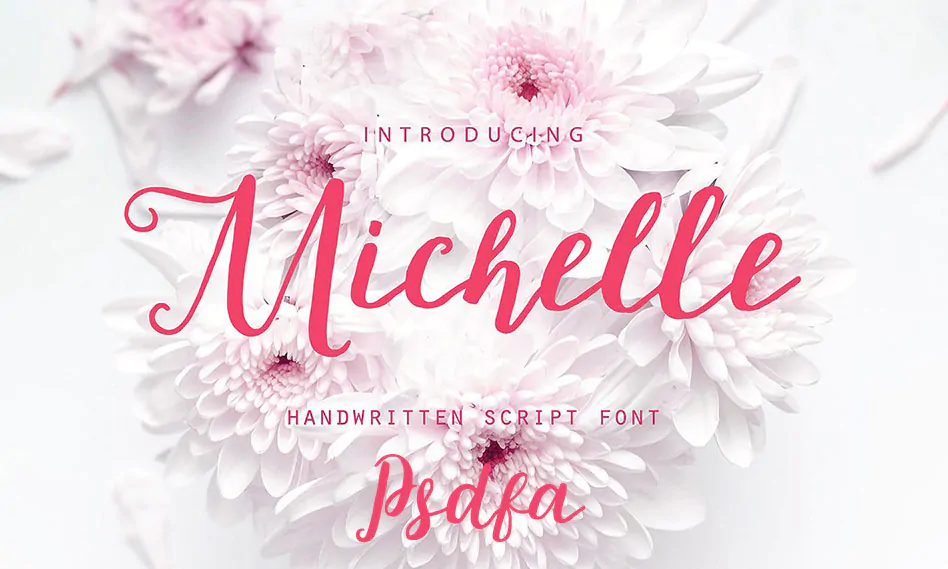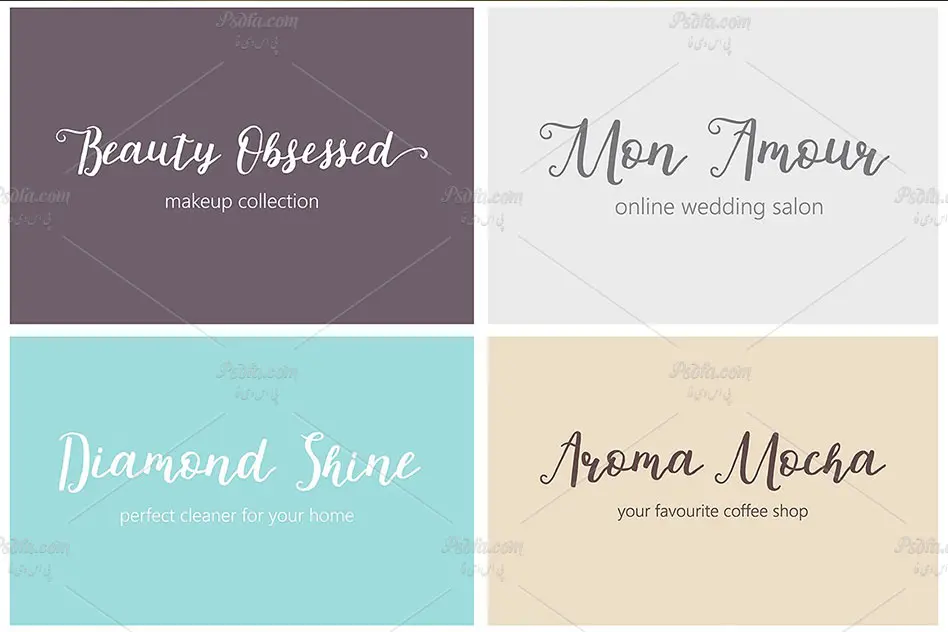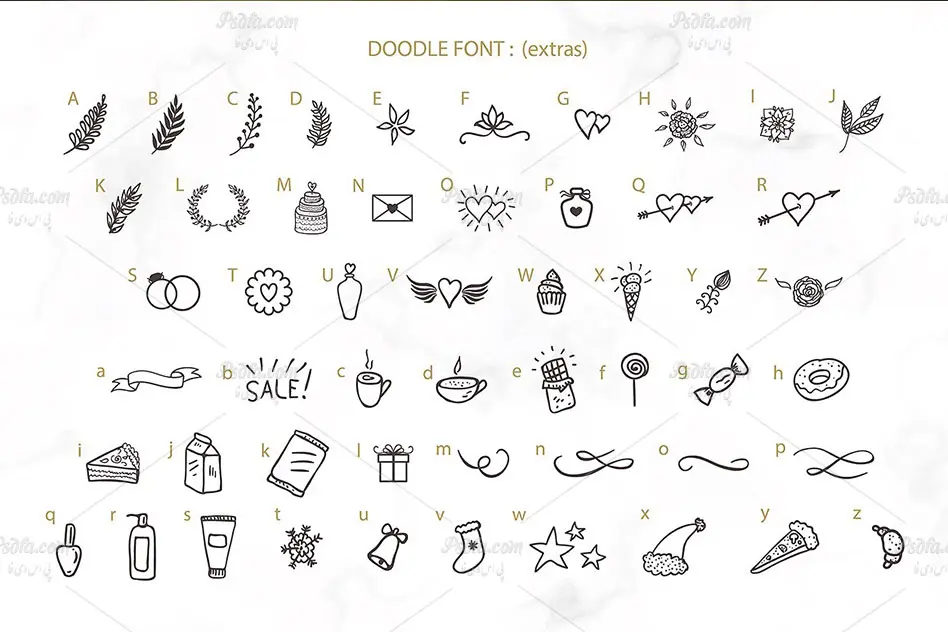
فونت انگلیسی mishelle script با طرح دستنویس
فونت انگلیسی mishelle script
در این مطلب شاهد فونت انگلیسی mishelle script با طرح دستنویس مناسب جهت استفاده در طراحی و گرافیک می باشید. توسط این فونت انگلیسی فوق العاده زیبا که با فرمت otf در سایت قرار گرفته است قادر خواهید بود طرح های گرافیکی فوق العاده زیبایی ایجاد کنید. شما با نصب این فونت در پوشه فونت های سیستم قادر خواهید بود از آن در تمام نرم افزارهای گرافیکی و ویرایشگر متن از جمله نرم افزار فتوشاپ ، مجموعه نرم افزار آفیس و … به طور مستقیم استفاده کنید. همچنین یک فونت سیمبل با نام doodle new نیز در مجموعه موجود است که از آیکون های آن می توانید در پروژه های خود استفاده کنید. فونت های وب mishelle script نیز با فرمت های woff و woff2 نیز در این مجموعه وجود دارد که از آن ها می توان در طراحی وب استفاده نمود.